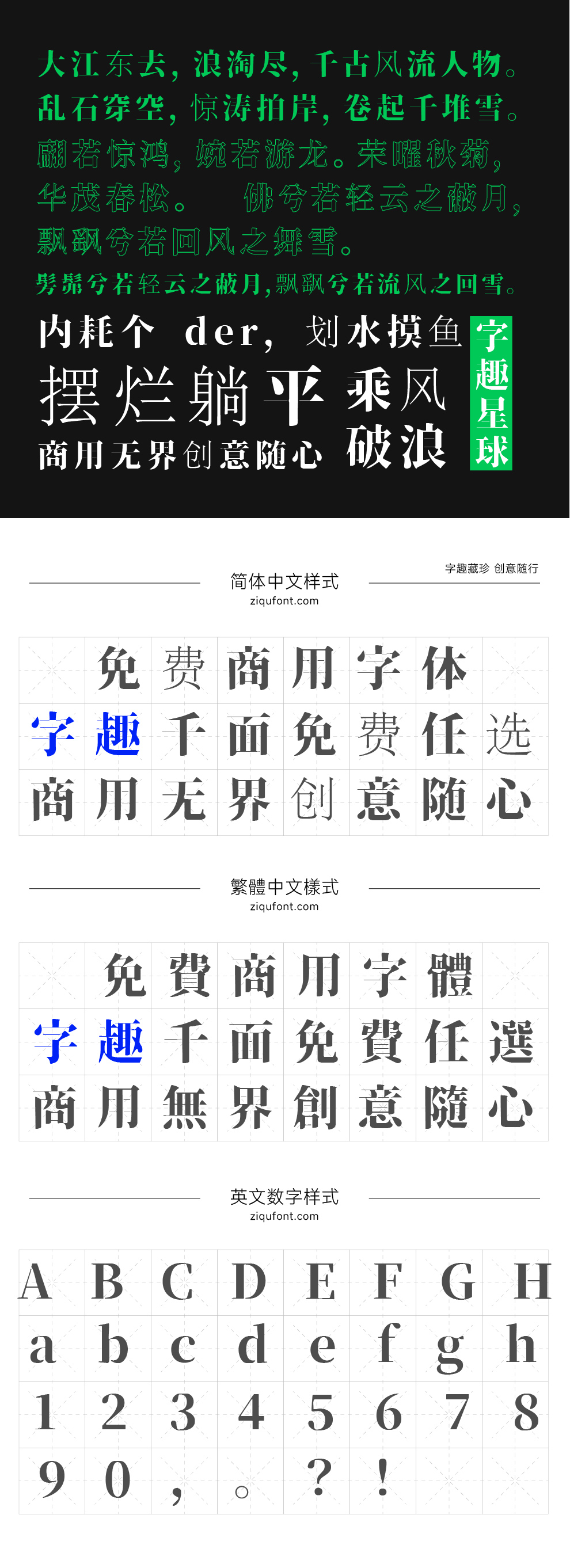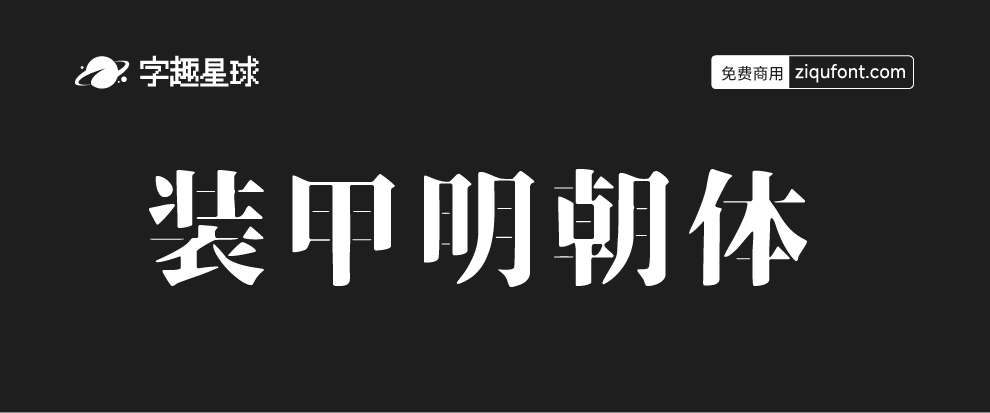
装甲明朝字体
字体介绍
「装甲明朝」(Soukou Mincho)看到这中文字体名称是不是觉得很霸气?如名称一样,字体风格硬朗有气派,以及拥有军队级的气氛、男人般凉意…… 若是拿来做越野车、大型装甲机车等玩具淘宝海报设计就非常适用了。
这是一款免费使用的中文字体,由日本网友从开源字体「思源宋体」改版而来,基于SIL Open Font License 1.1协议,但最终出来的效果却不大一样,装甲明朝体,将水平横线笔划修改得超细,在文字表现上,显得张力更强,十分霸气。
字体应用示例